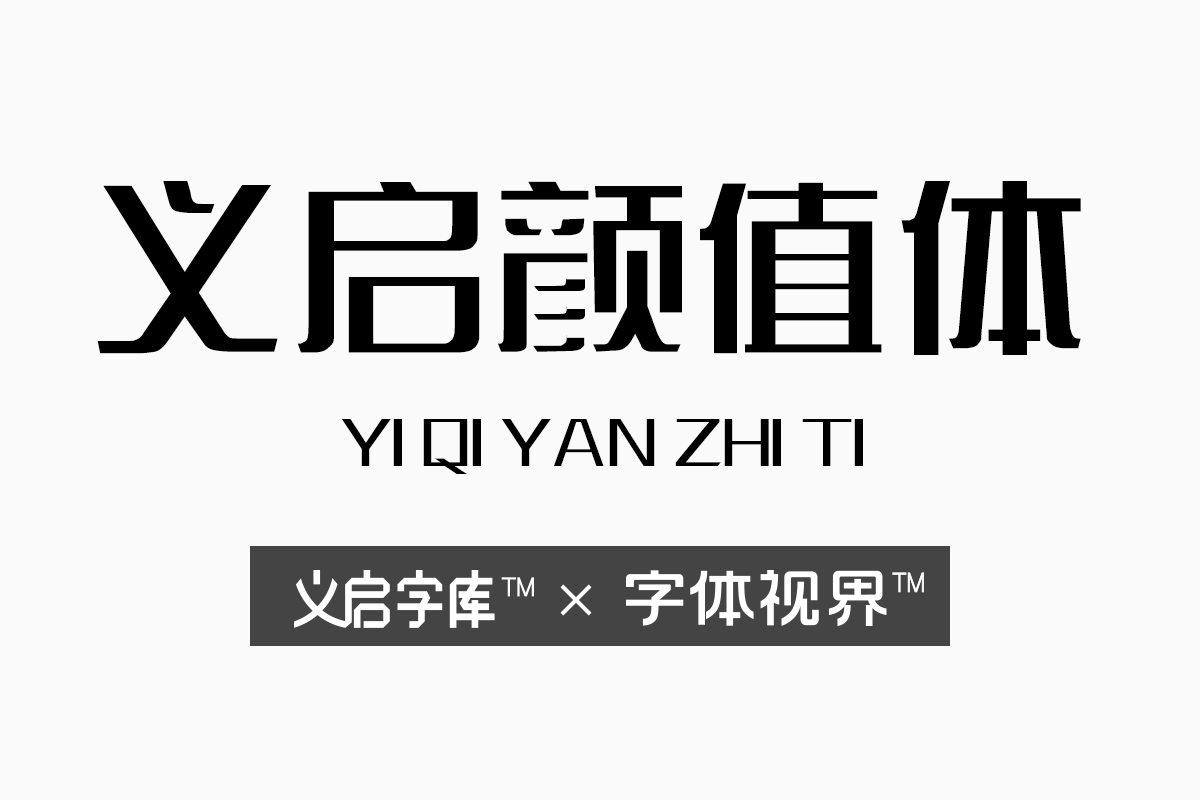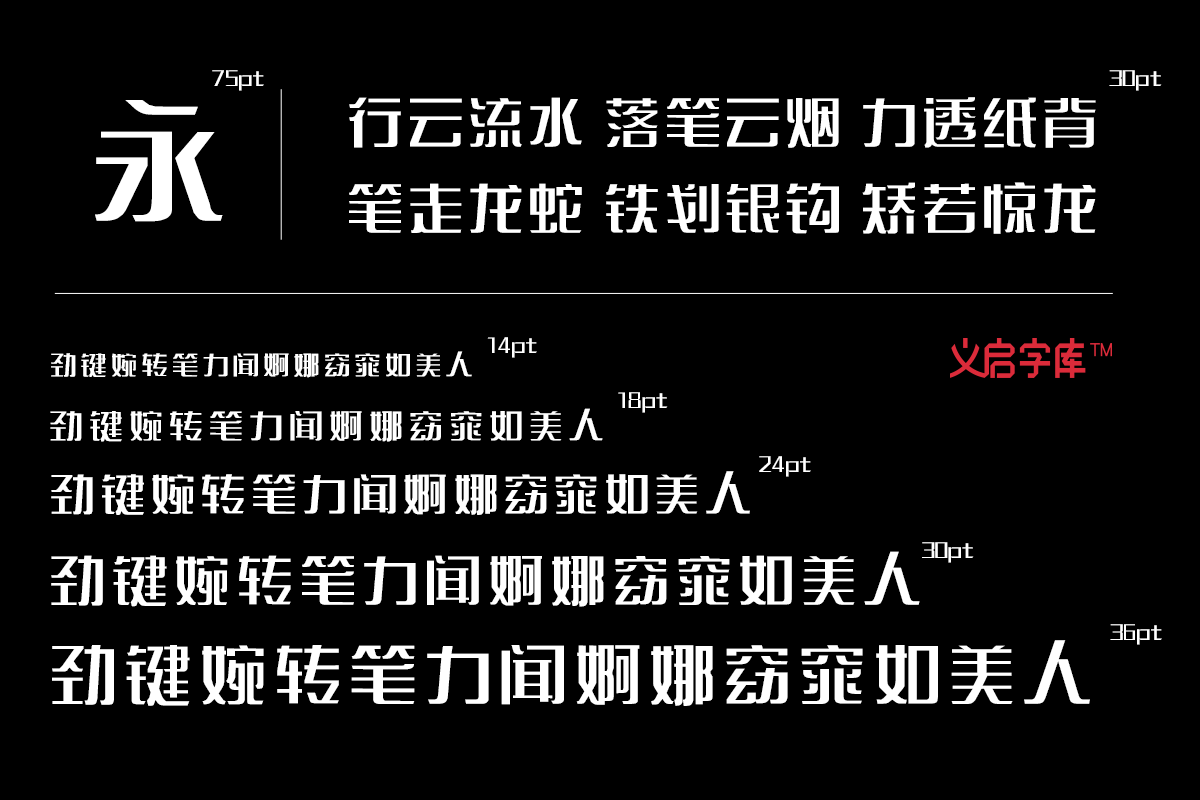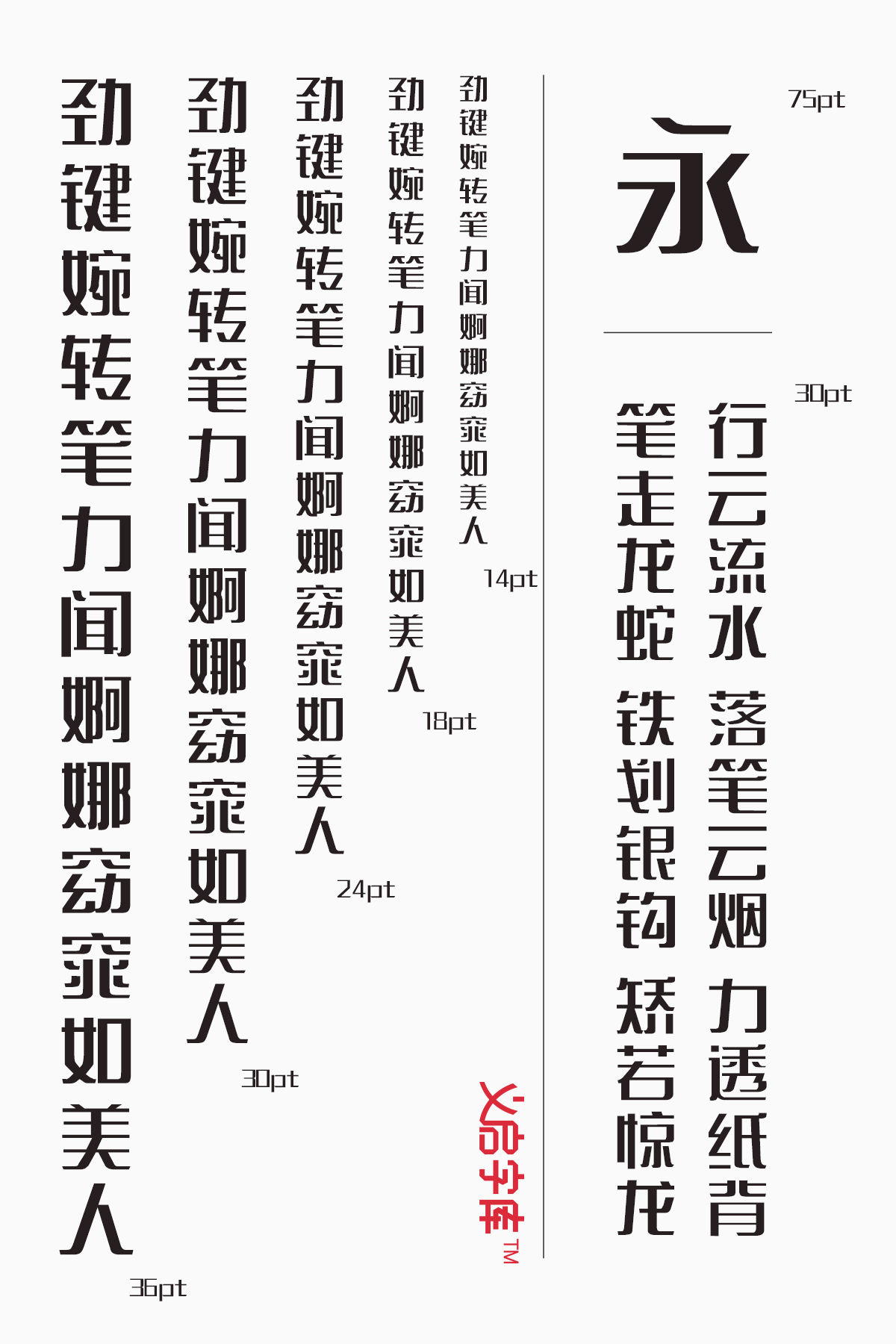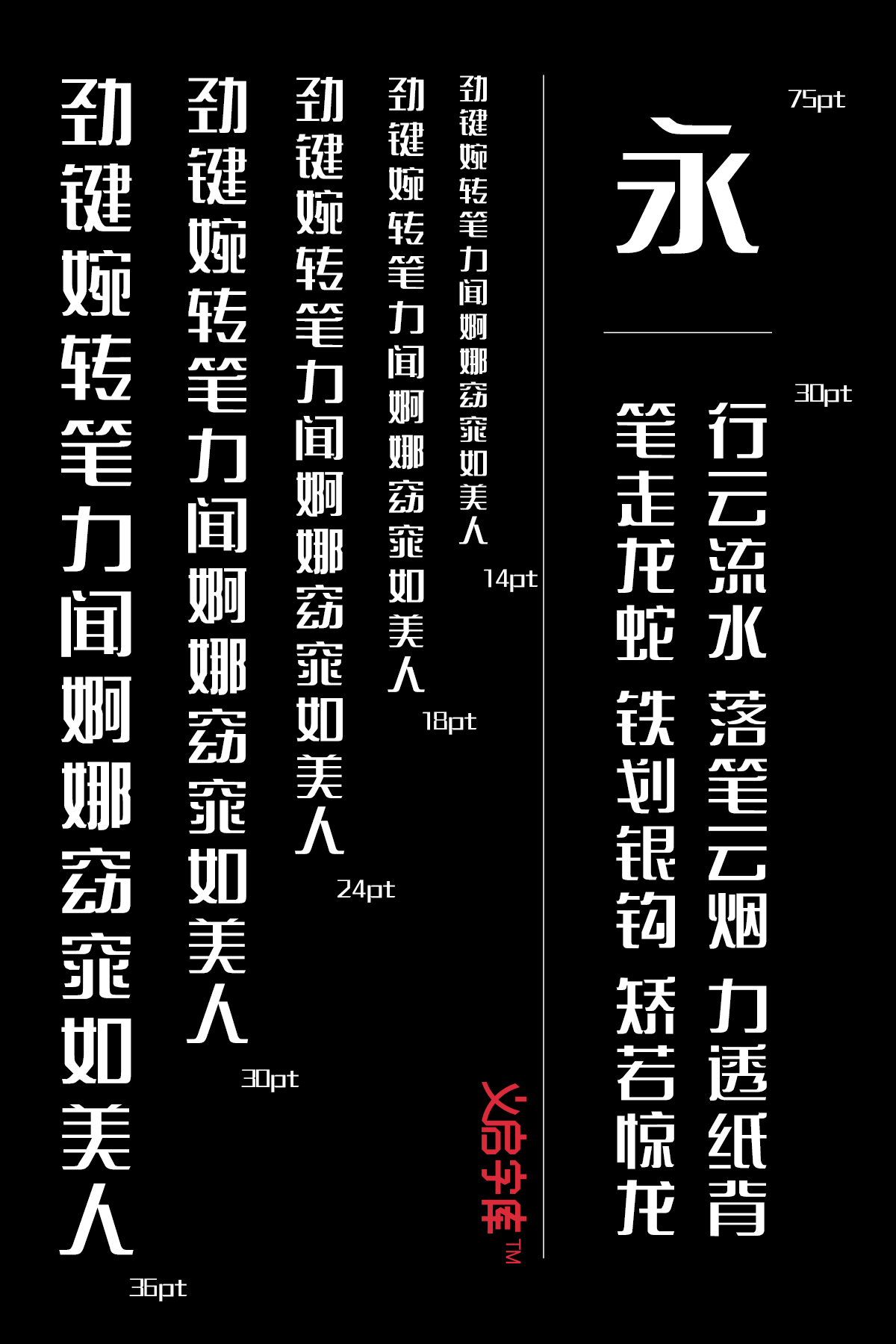
义启颜值体字体主要应用在哪些方面 临摹可以吗
在手机和电脑上可以找到很多的字体,像是义启一整个系列就可以在印品字库找到,而义启系列中有一种字体叫做义启颜值体字体,这一款字体其实并不常见,在平常应用的话倒是很少用到,但是却经常被用到一些重要场合,像是公司的信息展示或者是制作数据的时候,一些比较官方的场合经常会用到这种字体设计。
这种义启颜值体字体不是说它的颜值不高,而是说它的特性更符合一些大场合,当然小场合,像是普通的聊天也是可以使用的。
都知道在义启字库可以找到很多的字体,然后在这些字体中,总是可以找到符合自己审美标准的,但是有些人其实并不满足于只是在手机上看到符合自己口味的字体,甚至在手写的时候也想要写出来。
那么在义启字库的众多字体中,有哪些字体是可以临摹的?其实可以临摹的字体又很多,像是义启颜值体字体就是一种可以临摹、学习的字体,这种字体的应用范围很广,尤其是用到官方场合的话,还能够加分。